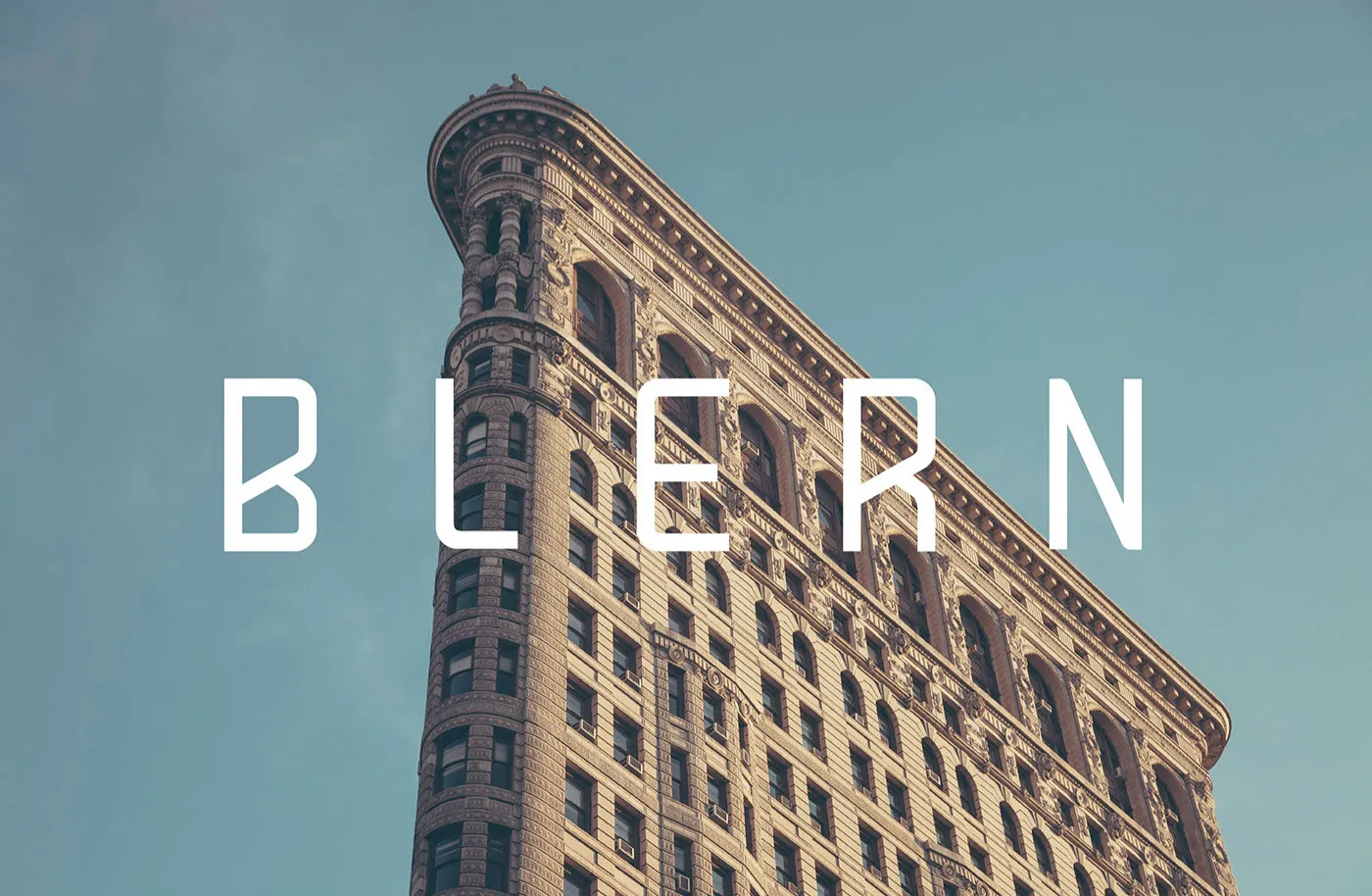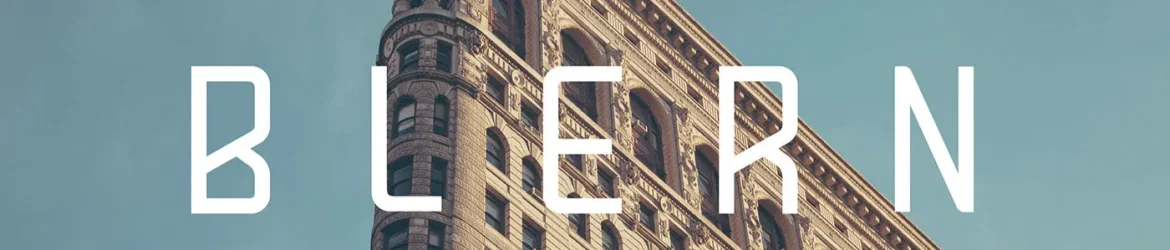
A Blern Typeface é uma elegante escolha para qualquer projeto que busque simplicidade e modernidade. Inspirada no estilo sans serif, essa fonte não carrega as convidativas curvas e detalhes de antigas fuentes romanas, proporcionando um design mais clean e direto. Seu designer Hamilton investiu em proporções perfeitas e linhas retas que se adaptam perfeitamente a diversos tipos de texto, oferecendo uma legibilidade excepcional em qualquer tamanho ou formato. Para quem busca uma solução minimalista para seu trabalho gráfico, a Blern é um excelente parceiro. Suas linhas nítidas e formas geométricas tornam o texto mais rápido de ler e permitem que ele brilhe de maneira ainda mais clara sobre backgrounds coloridos ou neutros. Seja para textos longos em um site ou para subtítulos em uma revista, a Blern Typeface garante que seu design seja moderno e contemporâneo.